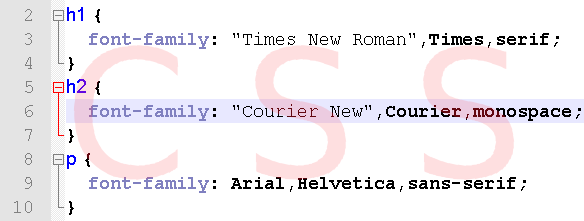
Guida CSS, scegliere il tipo di font
Guida CSS font-family
Qualche settimana addietro abbiamo visto il ruolo svolto dai fogli di stile CSS nel definire aspetti grafici e tipografici di una pagina HTML. Con questa guida riprendiamo l’argomento analizzando più nel dettaglio il funzionamento dei CSS rispetto agli elementi tipici di una pagina web. Cominceremo in particolare con alcuni post dedicati alla gestione del testo.
CSS, scegliere il tipo di font
Un primo aspetto di un elemento di testo che è possibile definire tramite CSS è il tipo di carattere (o font) da utilizzare. A questo scopo si impiega la proprietà font-family seguita dalle indicazioni sul tipo di carattere da utilizzare. Supponiamo ad esempio di voler definire il tipo di font da utilizzare con l’elemento ‘P’ di HTML (paragrafo di testo). Utilizzeremo una sintassi di questo tipo:
p {font-family: font-1, font-2, font-3, famiglia-font;}
La proprietà font-family così costruita indica al browser di visualizzare i paragrafi di testo utilizzando il tipo di carattere font-1. Se questo non fosse disponibile nel sistema operativo il browser utilizzerà il secondo font della lista (font-2) e via di seguito. L’ultimo elemento della lista svolge una funzione differente ed indica al browser di utilizzare il carattere predefinito appartenente ad una certa famiglia di font. Questa formulazione apparentemente sovrabbondante serve a garantire una buona rappresentazione del testo in funzione dei tipi di carattere effettivamente disponibili in ogni sistema operativo.
Famiglie di font e CSS
Per meglio comprendere quanto detto analizziamo questo spezzone di codice CSS:
h1 {font-family: "Times New Roman", Times, serif;}
h2 {font-family: "Courier New", Courier, monospace;}
p {font-family: Arial, Helvetica, sans-serif;}
Per l’elemento H1 di HTML si è scelto l’uso di font con grazie indicando due tipi di caratteri di questo tipo (Times New Roman e Times) e la famiglia che li rappresenta (serif). Osserviamo che il nome del font va racchiuso tra virgolette (“) se contiene degli spazi. Per l’elemento P di HTML il CSS dell’esempio prescrive l’uso di caratteri senza grazie (sans-serif) L’elemento H2 mostra infine l’impiego di caratteri a spaziatura fissa (monospace).